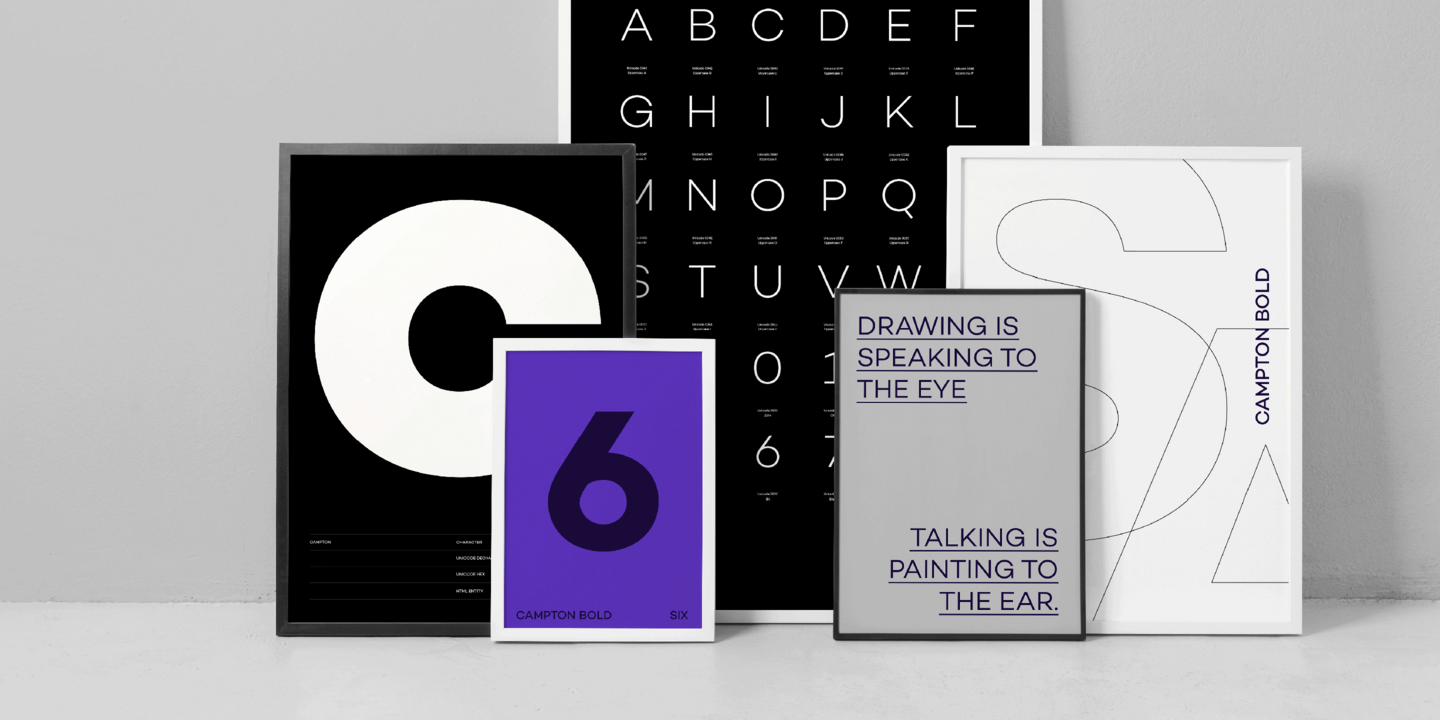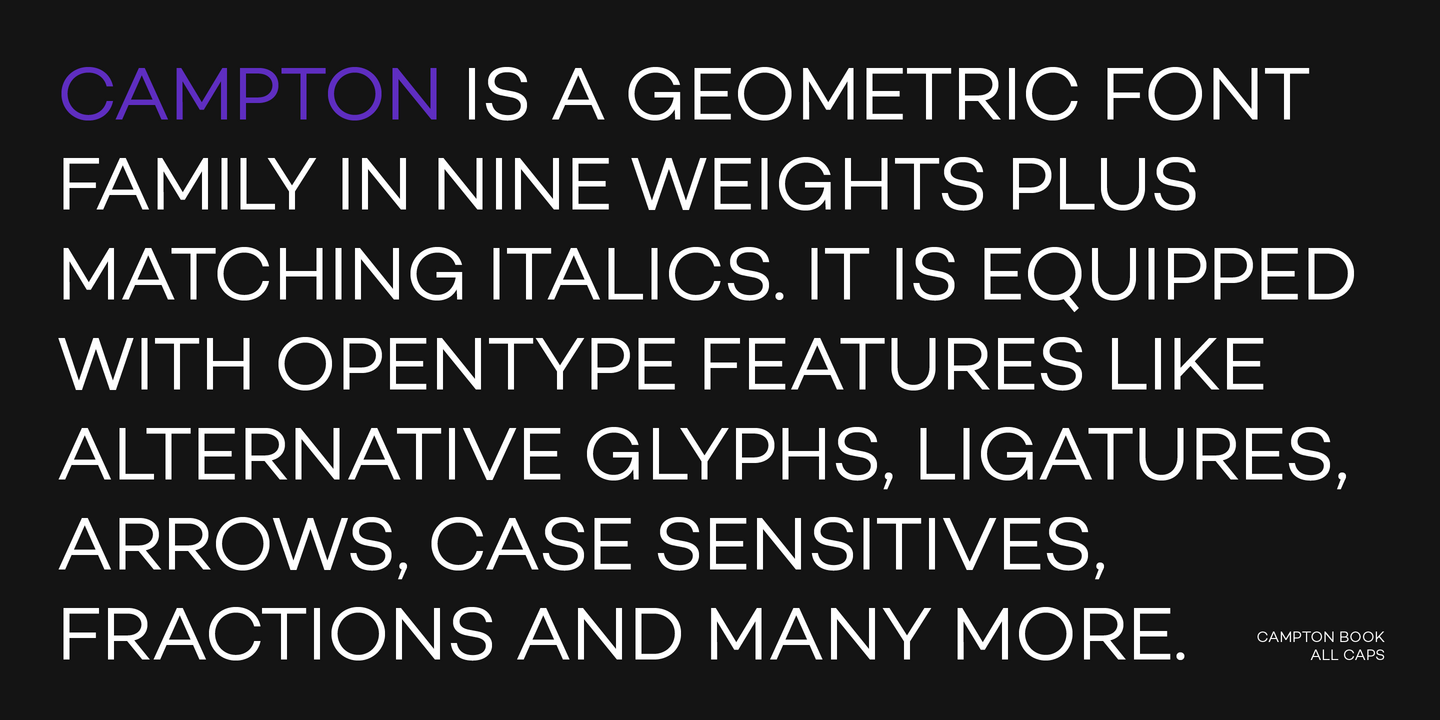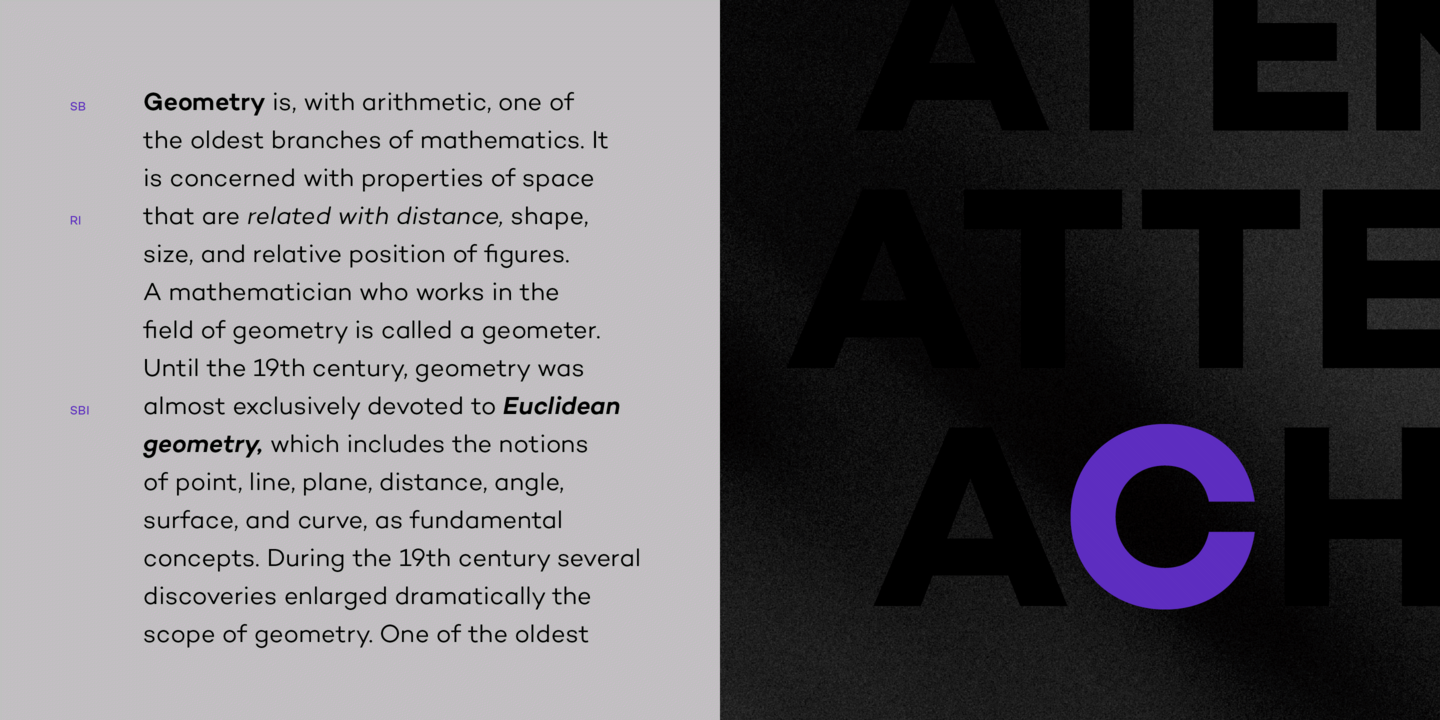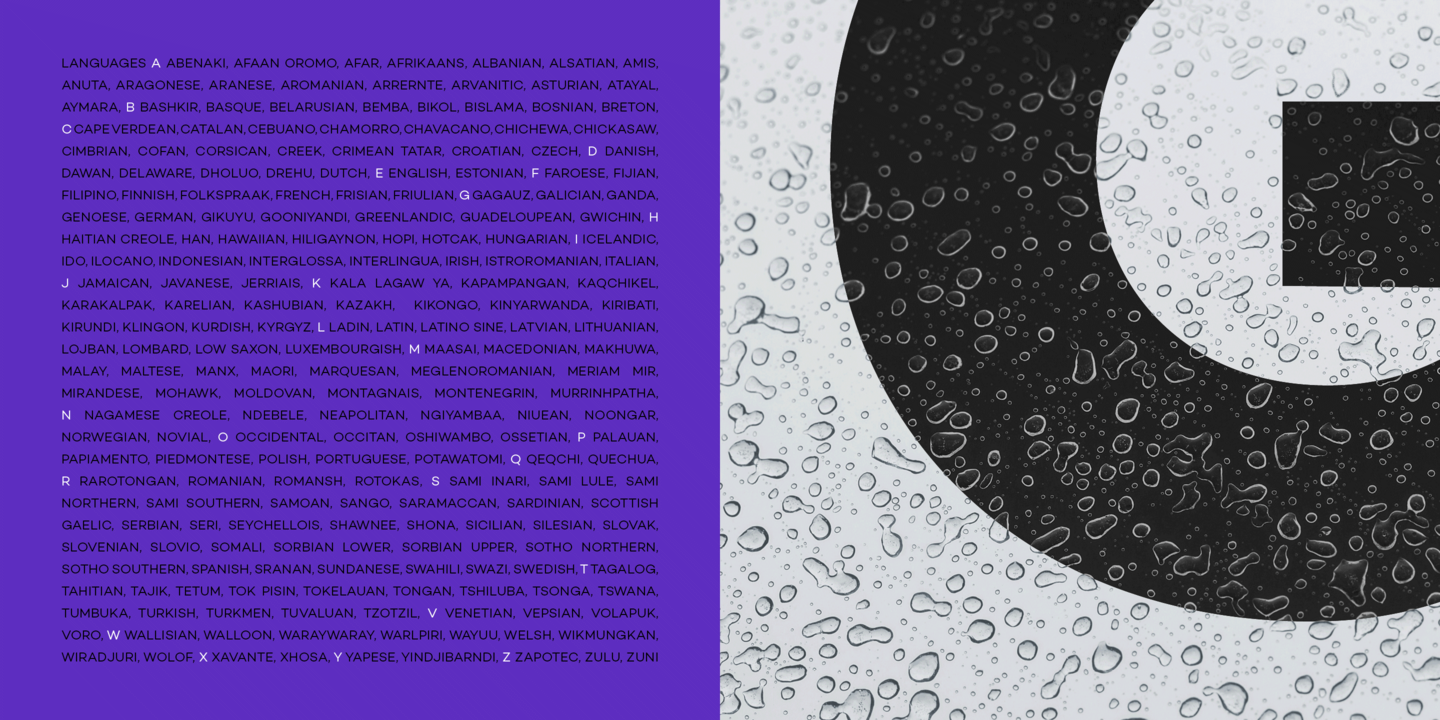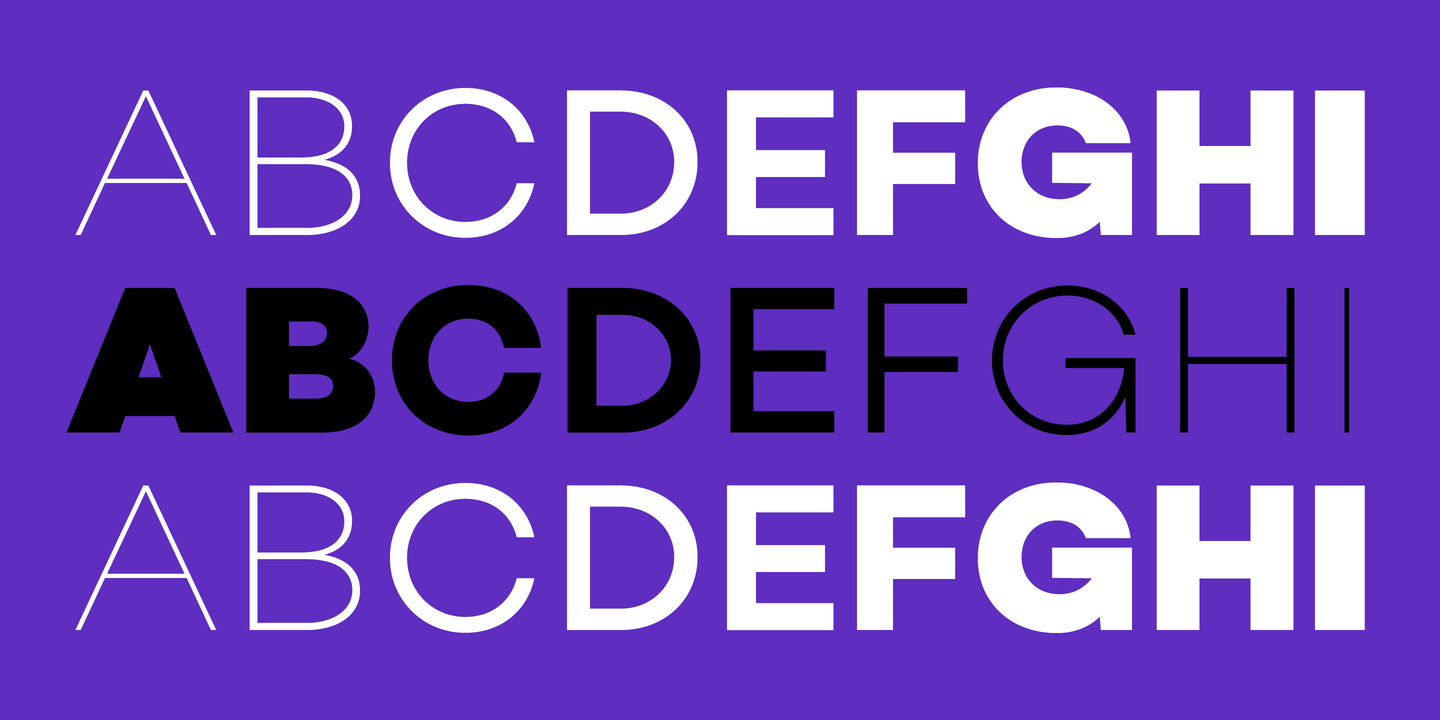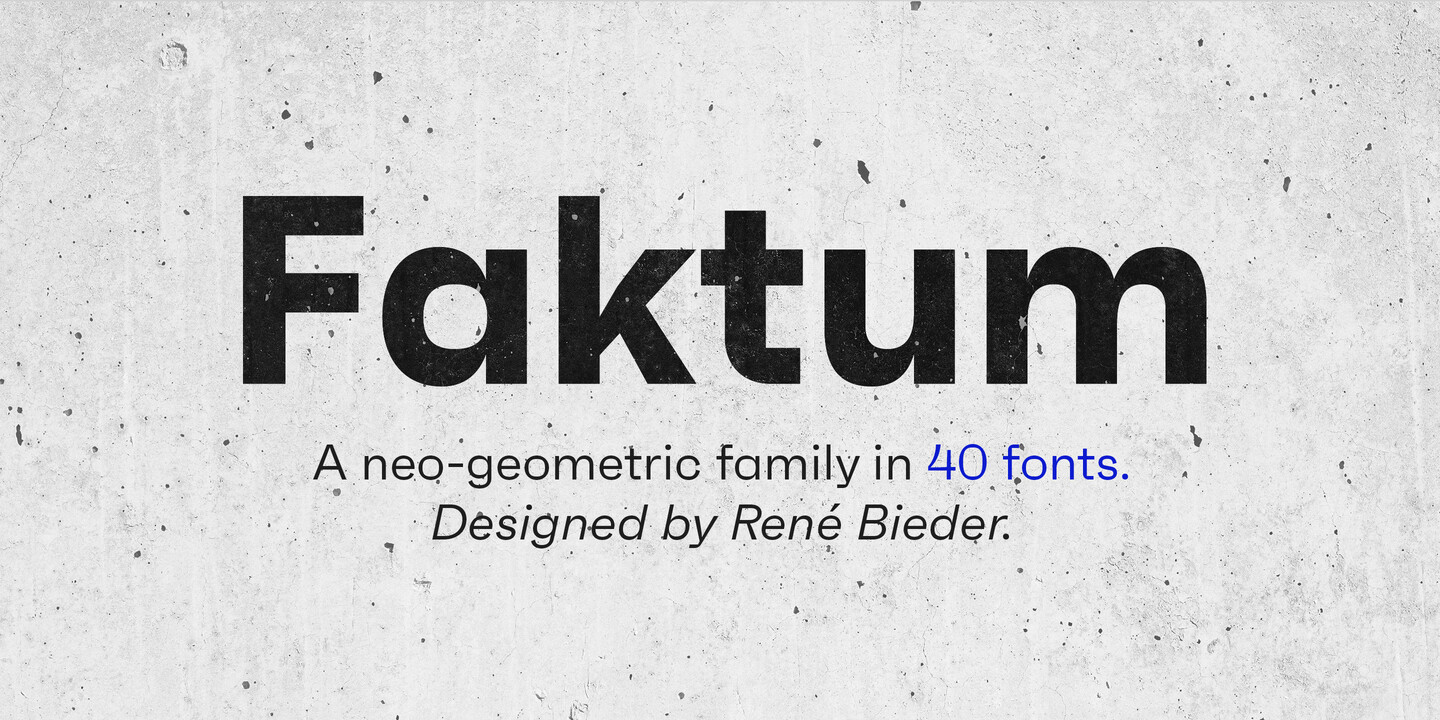
Polices de Rene Bieder.
Le Studio René Bieder est un cabinet de typographie et de design graphique basé à Berlin. Depuis 2012, René Bieder développe des familles de police à succès comme Campton ou Galano et des polices personnalisés pour de petits et grands clients.
Campton est une famille géométrique police . Elle s'inspire de différentes sources du début du XXe siècle telles que Futura, Akzidenz ou Gill Sans, tout en les combinant avec des éléments contemporains tels que des largeurs proportionnelles et une hauteur de x modérée. Le résultat est un regard moderne et frais sur le genre géométrique qui convient parfaitement aux applications de conception graphique allant de l'éditorial et du design d'entreprise au web et au design d'interaction. La famille se décline en neuf graisses, avec des italiques assorties, et est équipée d'une large gamme de fonctionnalités opentype.
Le Galano Grotesque est un sans géométrique dans la tradition du Futura, de l'Avant Garde, de l'Avenir, etc. Elle a un côté moderne qui est le résultat d'une harmonisation de la largeur et de la hauteur, en particulier dans les lettres minuscules, afin de favoriser la lisibilité. Le Galano Grotesque se veut une arme universelle, non seulement parce qu'il convient parfaitement aux titres, aux copies courtes et longues, mais aussi en raison de sa subtile neutralité. Il est disponible en 10 graisses différentes avec des italiques assortis et est équipé d'un ensemble de fonctionnalités opentype puissantes, y compris glyphs, fraction, flèches, ligatures et bien d'autres encore. Un jeu de caractères étendu, prenant en charge les langues d'Europe centrale, occidentale et orientale, complète la famille.
Faktum est une exploration du genre sans géométrique, inspirée par l'architecture et la décoration intérieure modernes du milieu du siècle dernier. La combinaison de lignes claires, de courbes organiques et de formes géométriques, très prisée par les designers et les architectes du deuxième tiers du XXe siècle, a donné l'impulsion à un design aux racines modernistes et à la finition contemporaine.
La famille se décline en 4 largeurs (XCon, Con, Normal et Wide) et 8 graisses, plus les italiques correspondantes, avec une large gamme de caractères alternatifs et de caractéristiques opentype comme les ligatures discrétionnaires, les formes sensibles à la casse, les différents jeux de chiffres et bien d'autres encore. Grâce à ses lignes épurées et à sa structure légèrement organique, Faktum s'adapte parfaitement à toutes les tailles et à tous les environnements, fonctionnant soit comme un support sobre police dans de longs paragraphes, soit comme un acteur principal dans des titres puissants.
L'histoire de Freigeist est un voyage dans le passé, jusqu'aux premiers grotesques polices et bien avant que l'Helvetica et autres ne deviennent la norme polices dans les systèmes d'exploitation. Car ce que nous considérons comme acquis aujourd'hui est le résultat de l'innovation et de l'esprit pionnier de fonderies de caractères telles que Caslon ou Stephenson Blake au XIXe siècle, dont les dessins expressifs sont pour la plupart oubliés aujourd'hui. La famille Freigeist capture cet esprit sauvage - d'où son nom (allemand pour "esprit libre") - et le place dans un contexte contemporain, ce qui donne une famille aux multiples facettes avec un large éventail d'applications, police styles et caractéristiques pour la composition moderne.
Magnat est une sans contrastée qui s'inspire des dessins du début du vingtième siècle et les développe dans un design contemporain élégant et distinctif. Des éléments ludiques tels que l'oreille incurvée du g minuscule ou la longue queue du Q majuscule rompent la rigueur et ajoutent du caractère. La combinaison d'ouvertures fermées et de traits contrastés crée une apparence générale élégante et distinctive.
Le Studio René Bieder est un cabinet indépendant de graphisme et de typographie basé à Berlin, spécialisé dans le développement de caractères pour la vente au détail, de solutions personnalisées police et de conseils en matière d'image de marque. Tous les produits polices sont basés sur l'idée de créer des outils uniques et puissants pour les marques et les individus, en combinant des connaissances historiques avec une approche contemporaine forte. Pour plus d'informations, veuillez consulter le site www.renebieder.com.
Concepteur de type
Rene Bieder
René est né et a grandi à Berlin. Avant sa première publication sur police en 2012, il a travaillé comme directeur artistique et designer pour de petites et grandes agences de publicité à Berlin pendant plus de dix ans. Encouragé par le succès de sa première publication de caractères (MyFonts Most Popular Polices of 2012), il a commencé à travailler sur d'autres conceptions et s'est finalement mis à son compte en 2014. Toujours en 2014, il a publié les familles Campton et Galano police qui figurent encore aujourd'hui dans la liste des 50 meilleures ventes sur Myfonts. Il compte parmi ses clients des marques telles que Disney et Penguin Books, le gouvernement de Nouvelle-Galles du Sud, plusieurs chaînes de télévision privées, Wacom, Bahlsen, Bumble et Discovery Channel. René travaille actuellement sur de nouvelles polices de caractères pour le commerce de détail et sur polices pour des entreprises de toutes tailles.